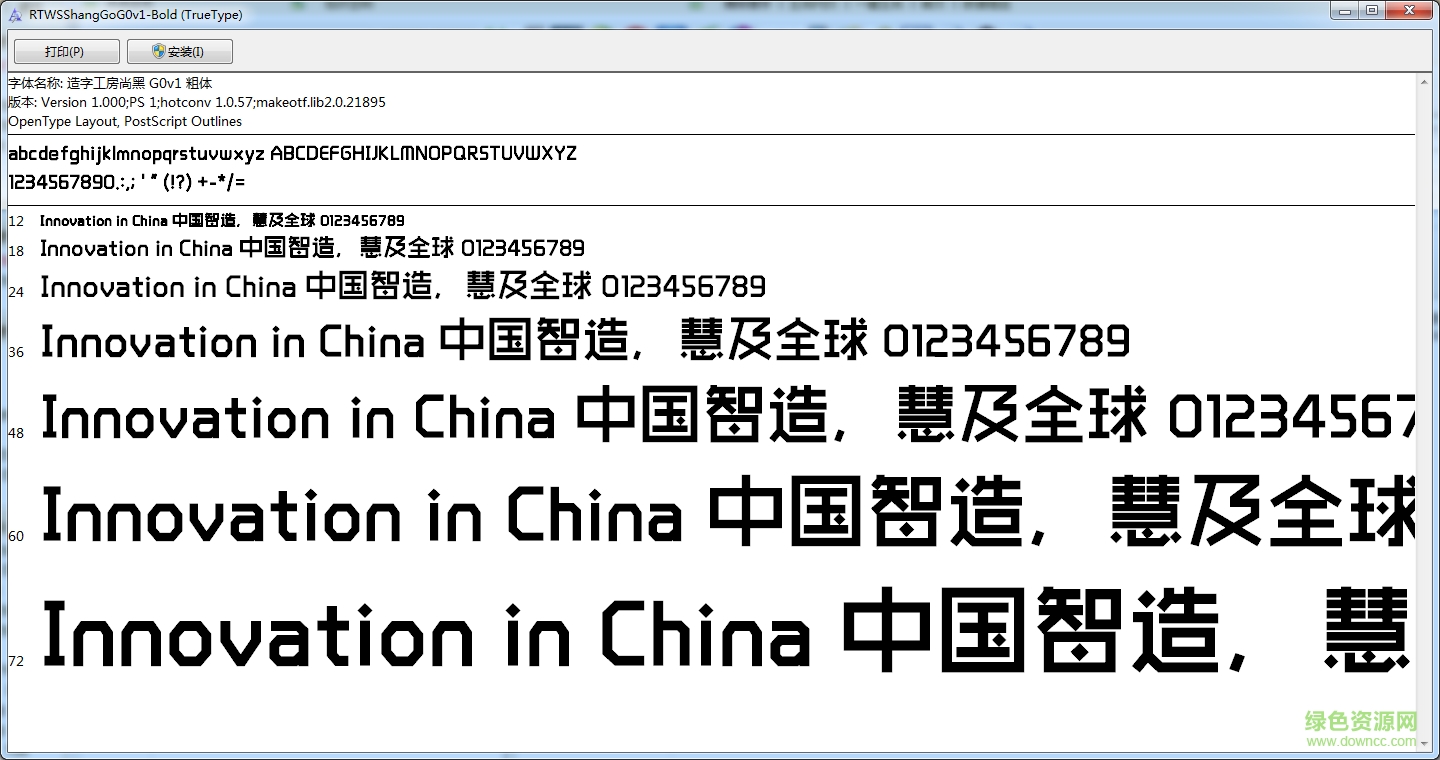
rtwsshanggogov1 bold 字體
rtwsshanggog0v1 bold字體又叫造字工房尚黑 g0v1 粗體,是一款形體干凈得體的黑體字體,筆畫(huà)勻稱(chēng)漂亮,結(jié)構(gòu)規(guī)整,實(shí)用性強(qiáng),需要的朋友快來(lái)綠色資源網(wǎng)下載吧!
黑體字體特點(diǎn)
設(shè)計(jì)首批黑體的時(shí)候,參照了有喇叭口裝飾的黑體,所以早期的Windows XP,Mac OS中的“中易黑體”和“華文細(xì)黑”都是帶有喇叭口的。
而另外一種有裝飾襯線的黑體,是參照人工用板刷寫(xiě)的黑體,因此在這些黑體當(dāng)中,豎筆、提點(diǎn)、撇等筆畫(huà)中會(huì)在起筆處帶有小圓點(diǎn)裝飾,例如“方正韻動(dòng)黑”正是這樣的字體!